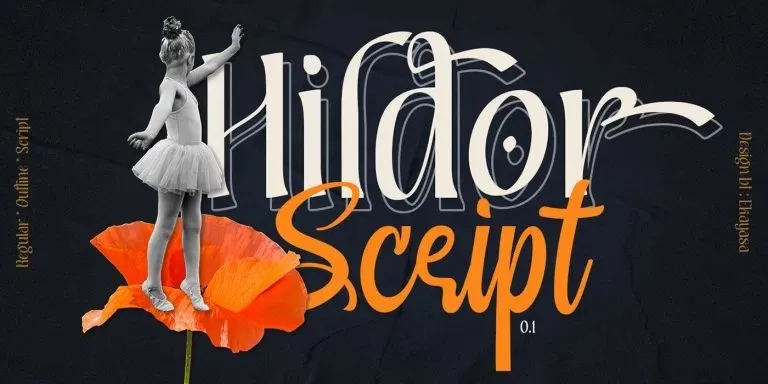
Hildor Font Duo – Fonte Grátis
Hildor Font Duo
A font Hildor Font Duo é uma descoberta única que combina duas faces distintas das mesmas fontes originais. Ela não apenas oferece a versão estilizada e delineada, mas também inclui um caráter mais natural e retrô do tipo de escrita manuscrita. Seja usada em conjunto ou sozinha, essa dualidade faz dela uma opção perfeita para qualquer projeto gráfico. A fonte traz todo o alfabeto maiusculo e minusculo, símbolos multilíngues, números, sinais de pontuação e ligaduras. Além disso, apresenta pequenas terminações menores que começam e finalizam as letras minúsculas, bem como os famosos swashes redondos para o coração. Esses detalhes finos são essenciais para conectar palavras ou letras em um estilo moderno, perfeito para cartas de casamento e personalizações únicas. Seja qual seja seu projeto, a Hildor Font Duo tem algo especial para oferecer.